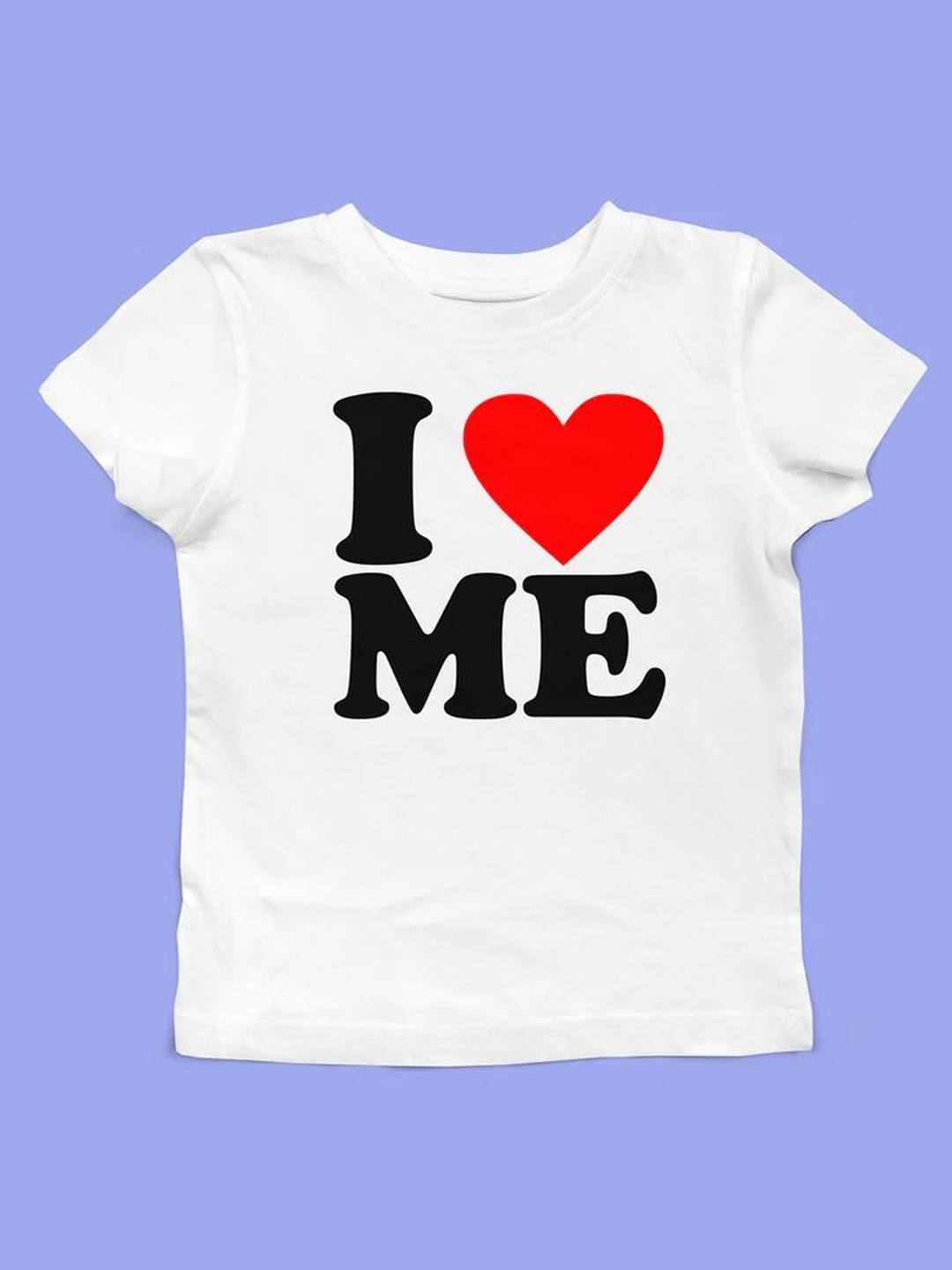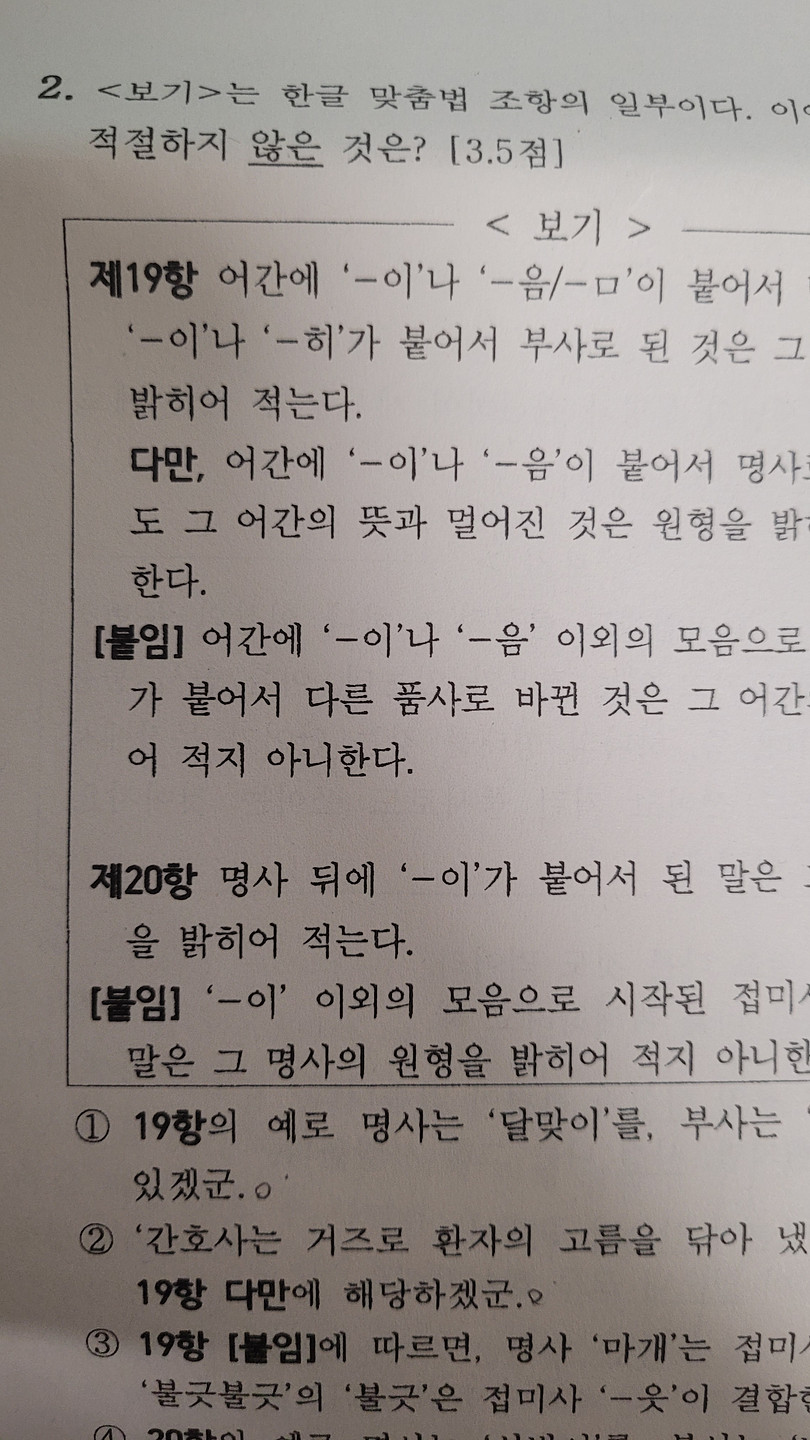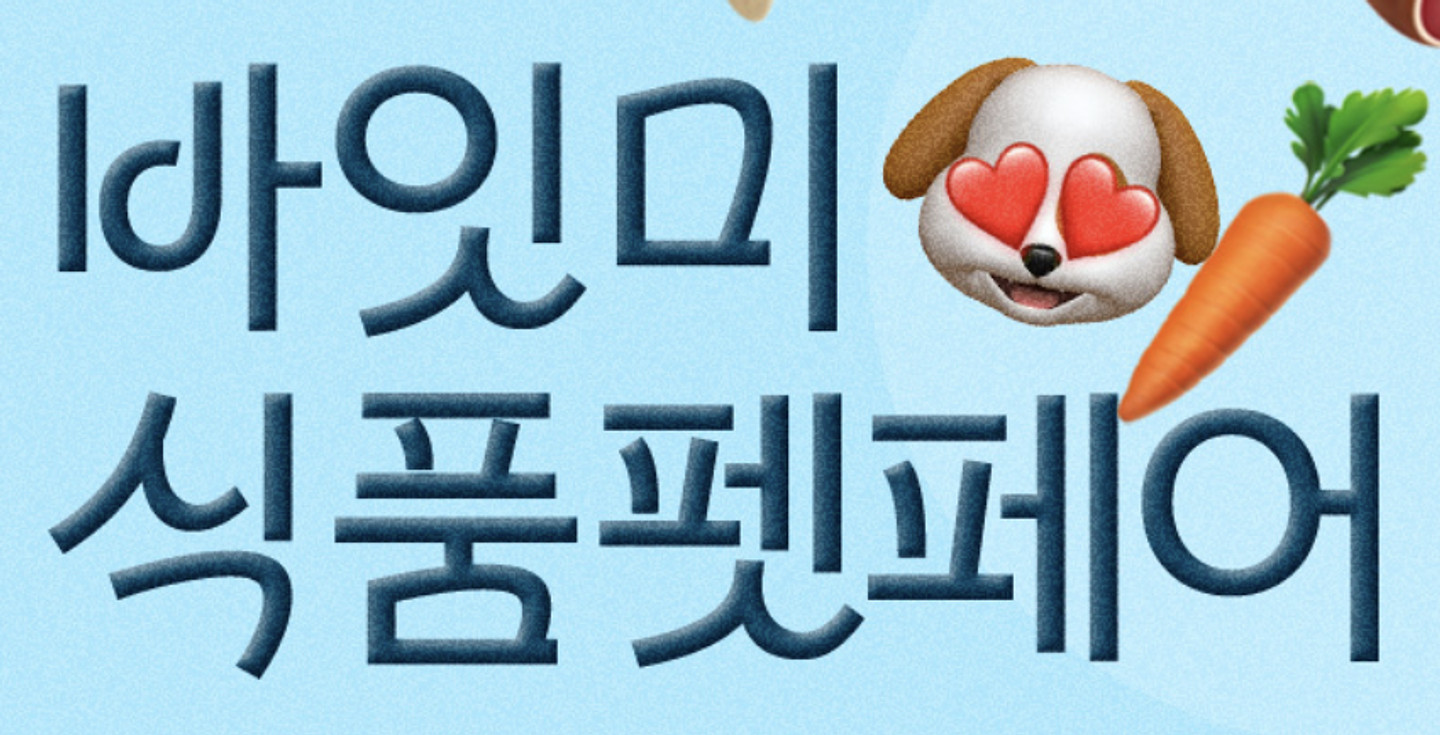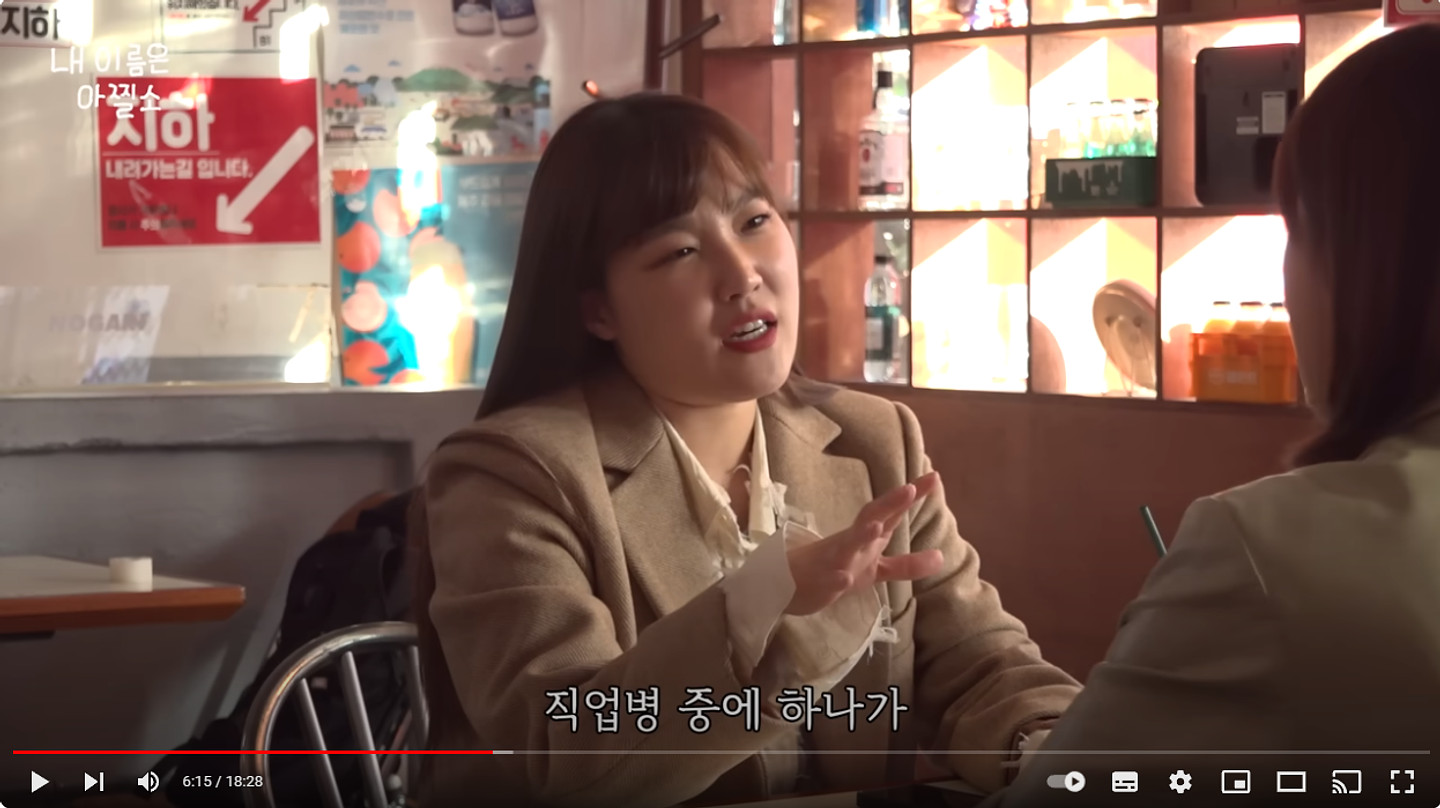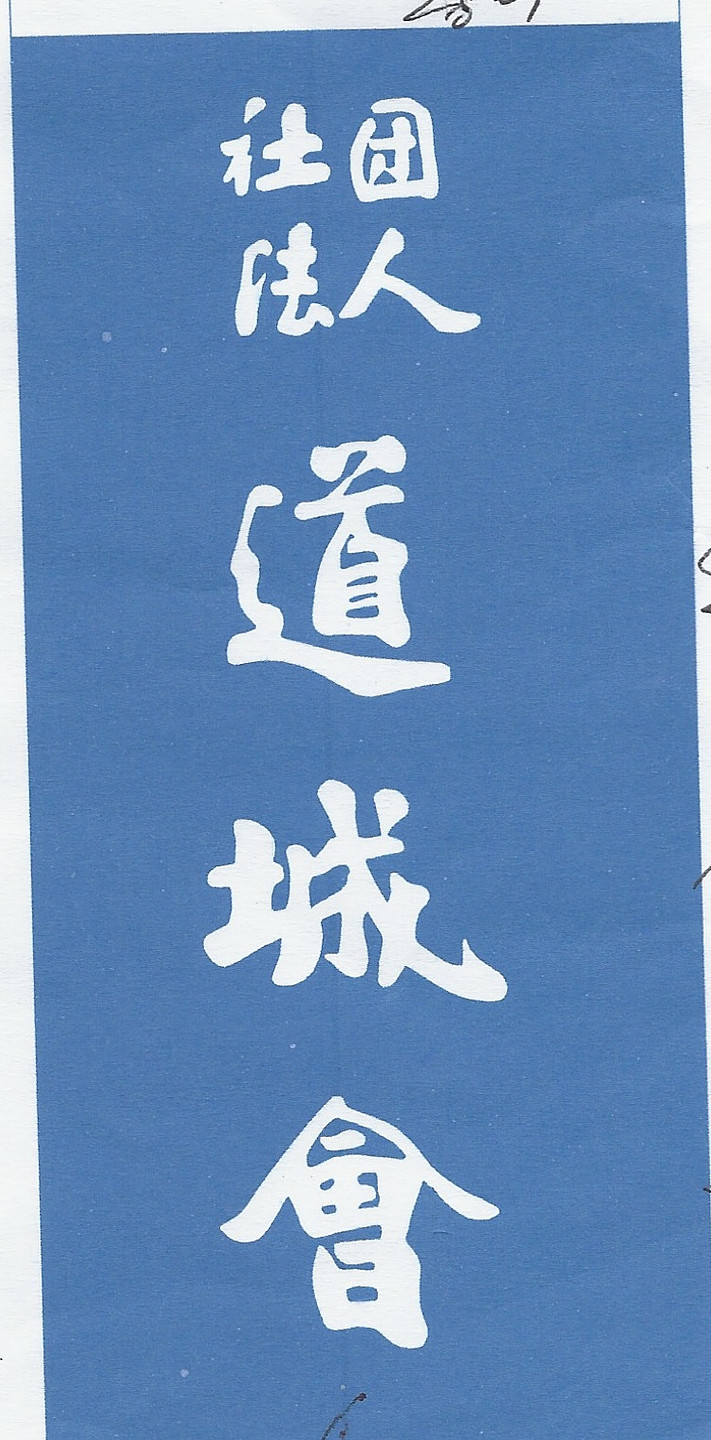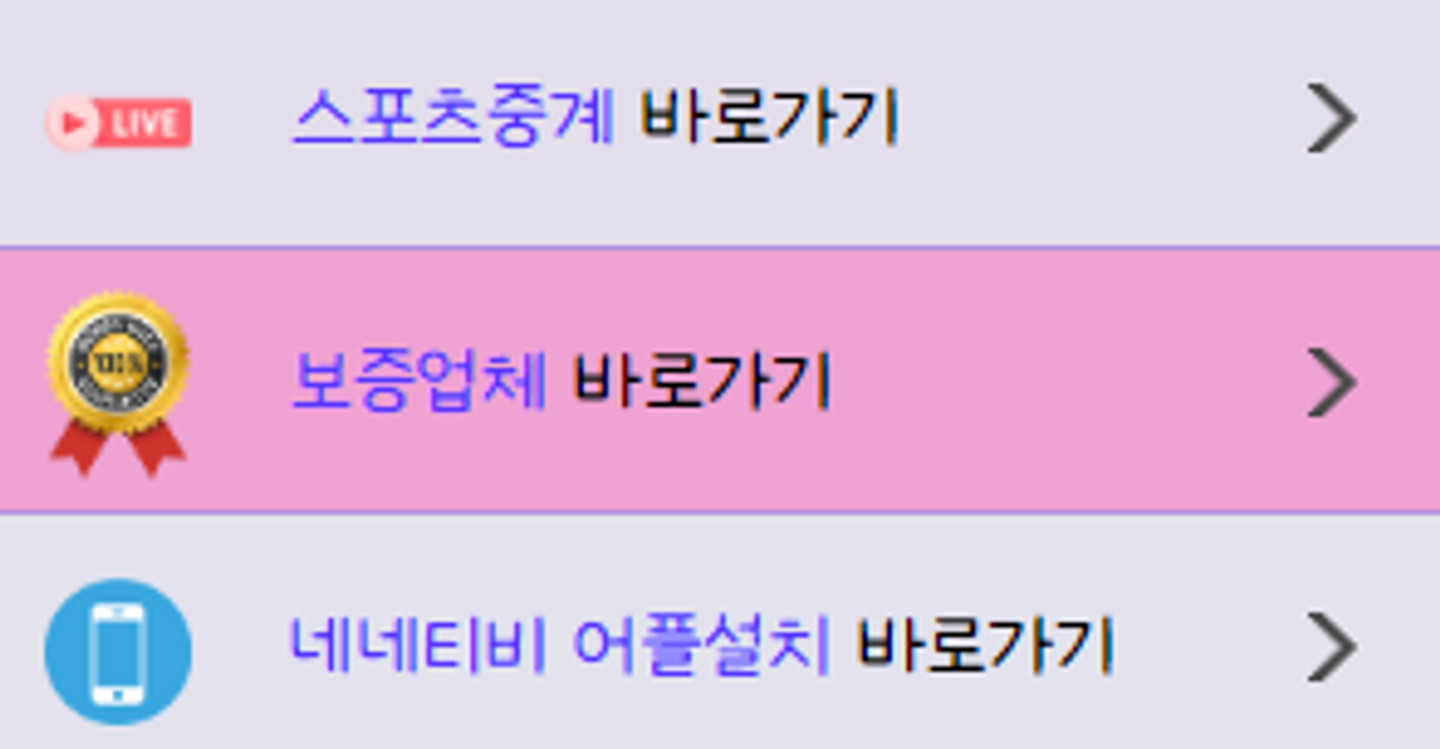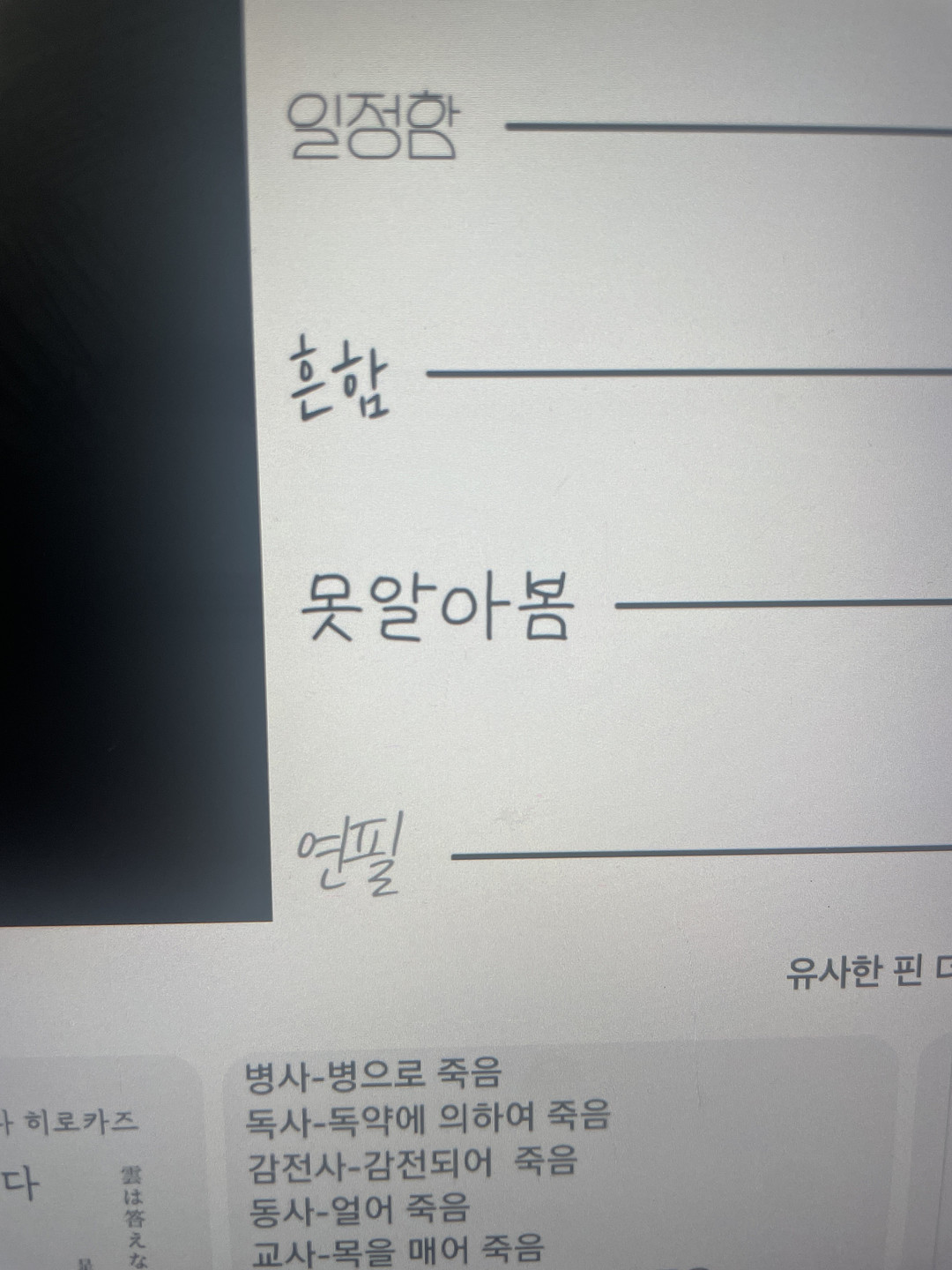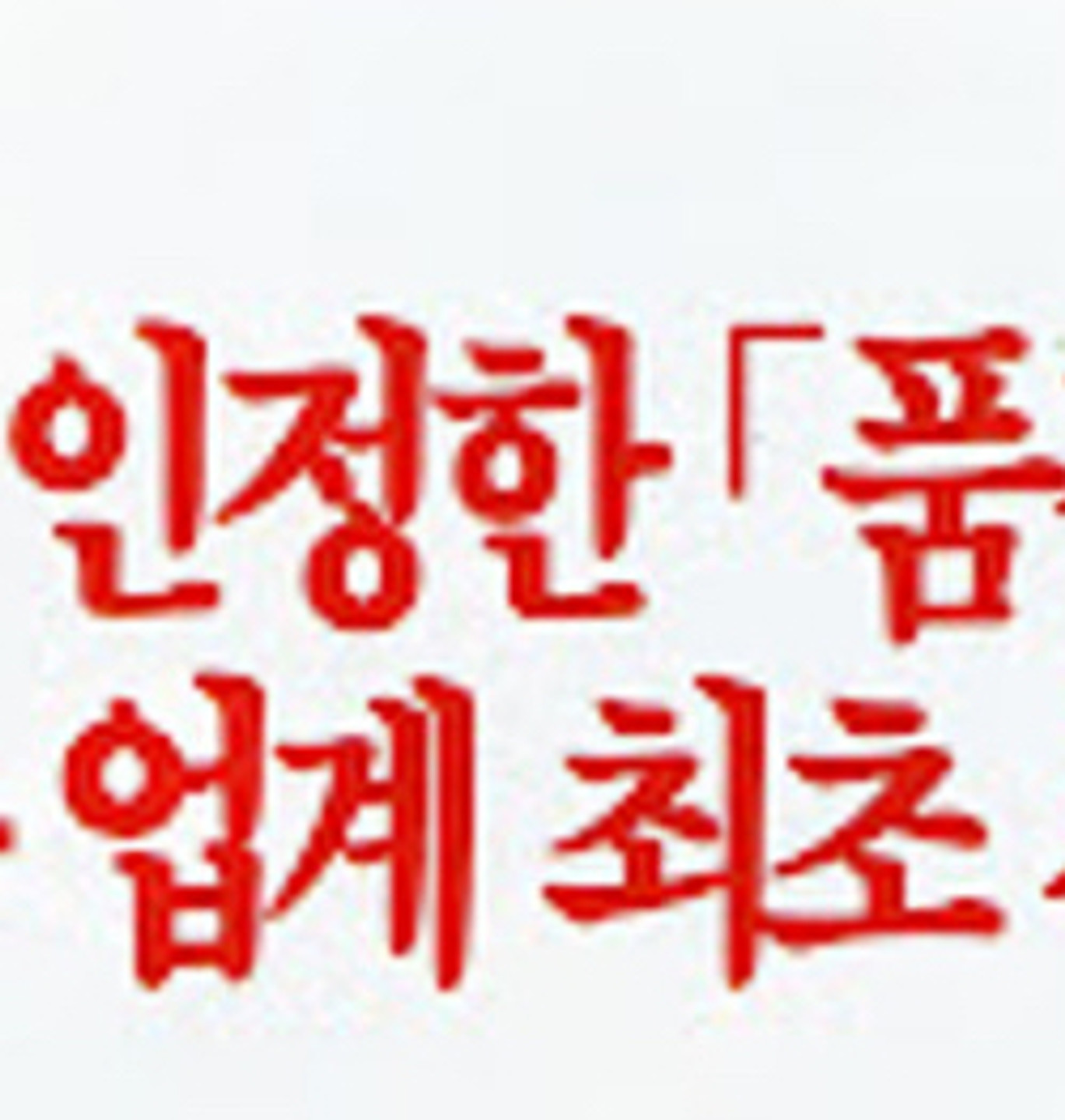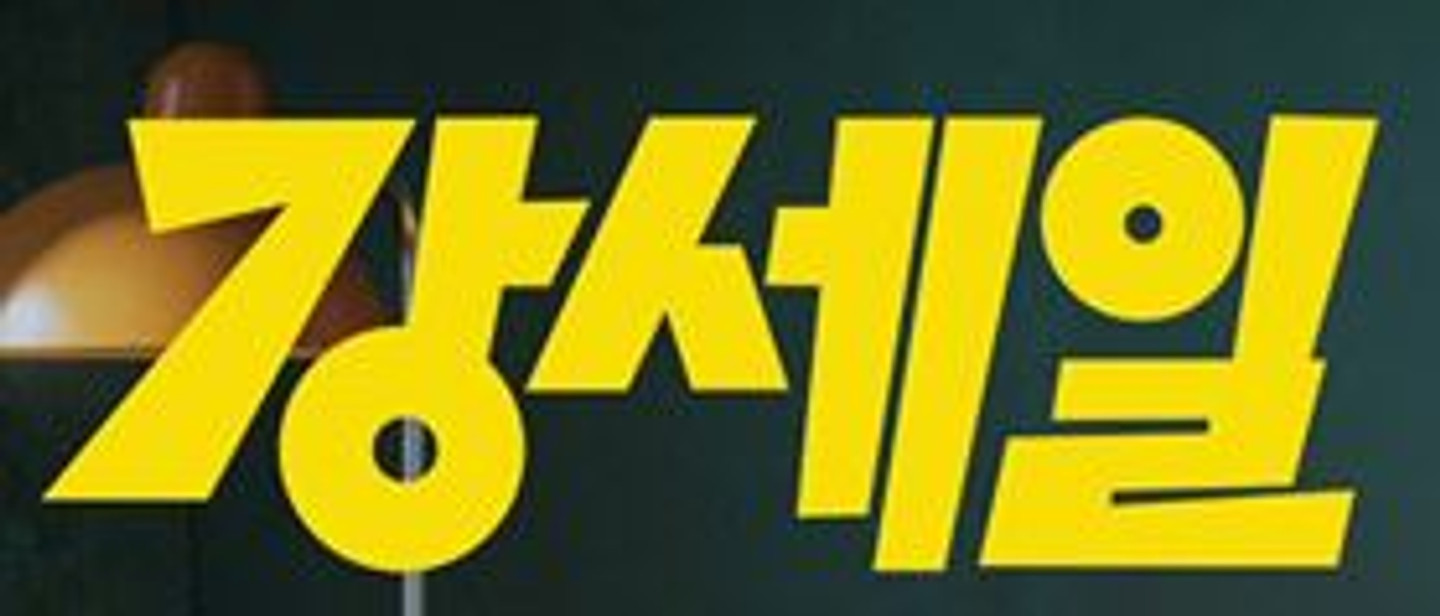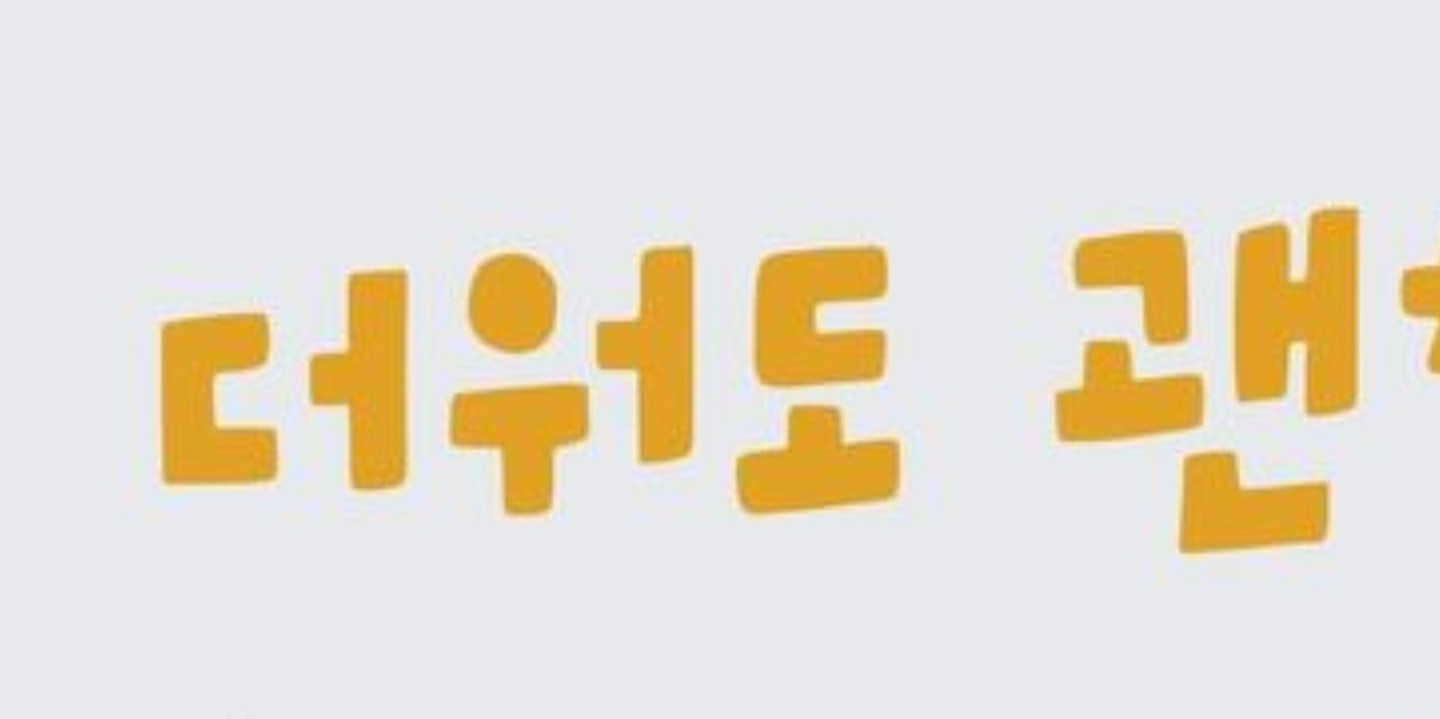
이 폰트 무슨 폰트인가요? ㅇ이 여우꼬리 같은 느낌을 줘서 궁금하네요.
이 폰트 알고싶어요!
폰트 궁금합니다 ㅠㅠ ~
사기당할 뻔 하셨다는 글의 폰트를 여쭙자니 좀 그렇지만...(문제 시 삭제하겠습니다) 혹시 해당 폰트에 대해 아신다면 답변 부탁드리겠습니다 감사합니다
롱블랙 글인데 폰트가 무엇일까요? 감사합니다
갤럭시같은데 아무리 찾아도 모르겠어요..
넷플릭스 자막입니다 폰트 뭘까요 !!?
이 폰트 이름이 뭘까요?ㅠㅠ급해요
https://une0221.cafe24.com/ 사이트에서 사용하는 영문 폰트인데 너무 예뻐서 어떤 폰트인지 알 수 있을까요?
이거 무슨 폰트인지 아시는 분? 최대한 바른 답변 부탁드립니다
폰트 간절히 찾고 싶습니다. 부탁드립니다.
게임 배너입니다. 폰트 알 수 있을까요?
이 폰트 찾아줘
흘린 붓글씨입니다.
이렇게 숫자 끝부분들이 삐죽? 한 폰트가 별도로 있나요?ㅠㅠ
쿠보타 1920 준마이 다이긴죠 (久保田 1920 純米大吟醸) 술 원목 포장> 이름에 있던 건데 폰트를 모르겠어요 ㅠㅠ
이거 폰트 뭔가요>??
궁금해요~
폰트궁금해요
위에 큰 글자와 아래 작은 글자 각각 폰트 뭔가요?
폰트와 효과 궁금합니다
폰트와 효과가 궁금해요
폰트뭔가요
영문 한글 각각 폰트 궁금합니다
부럽태산 서체 궁금합니다!
카더가든 유튜브 보다가 궁금해서 질문 남깁니다! 그냥 산스네오 고딕인가요?
픽셀 폰트 궁금합니다 ~
해당 폰트 무슨 폰트인지 알 수 있을까요?
이미지 속 폰트 아시는 분 계실까요... 아무리 찾아도 안나오네요ㅠㅠ
국민은행 스타뱅킹 폰트 뭔지 궁금해요 ㅠㅠ
폰트 박사님 폰트 알려주세요
이거 무슨 폰트인지 너무너무 궁금합니다
이 폰트 무슨 폰트인가요??
여기서 한글부분 폰트 부탁합니다
리카리카 브랜드에서 사용하는 폰트 아시나요?
이거 무슨 폰트인가용??
타이틀 폰트 궁금합니다 지마켓산스인가요?
나의 완벽한 비서 스페셜 방송 자막에 나왔던 폰트 혹시 뭔지 아시나요?
정관장 1월 광고에서 행운의 편지 광고 폰트가 궁금합니다!
글씨체는 굵고 끝에 몇 군데는 둥근 부분이 있는데 어떤 폰트인지 찾아주시면 감사하겠습니다~~
창경센터에서 쓰이는 로고는 어떤 폰트인가요?
작은 자막 서체 궁금해요! 배민서체인가요?
위의 명조체와 아래의 명조체가 다른듯 한데, 위의 두가지 폰트 무슨체 일까요?
혹시 이 폰트 뭔지 알 수 있을 까요? ㅜㅜ 급해요
이거 폰트 뭔지 아시는분ㅠㅠ
이 폰트 이름이 무엇인지 알고 싶습니다.
혜리가 광고하는 비건쿠키 광고 폰트인데 뭘까요?
문의 드립니다. MBC 질문들에서 사용된 폰트입니다. 무슨 폰트일까요?
혹시 이 폰트 이름도 좀 알 수 있을까요?
킹덤컴2에 나오는 폰트인데 굴림??인거같은데 '얼'자가 아무리봐도 기본굴림이 아닌거같기도 해서요 ㅠ_ㅠ 튜 도 기본 굴림체는 ㅠ가 살짝 꺾이는데 저건 일자입니다! 무슨폰트인가요 ㅠㅠ 아시는분...
폰트이름
두꺼운 고딕폰트 이름이 뭘까요?
무슨 폰트인가요???????
요거 폰트 뭔가여?? ㅜㅜㅜ
무슨 글씨체일까요? ㅠㅠ 부탁드립니당!!
두껍고 둥근 이 폰트 이름이 뭔가요?